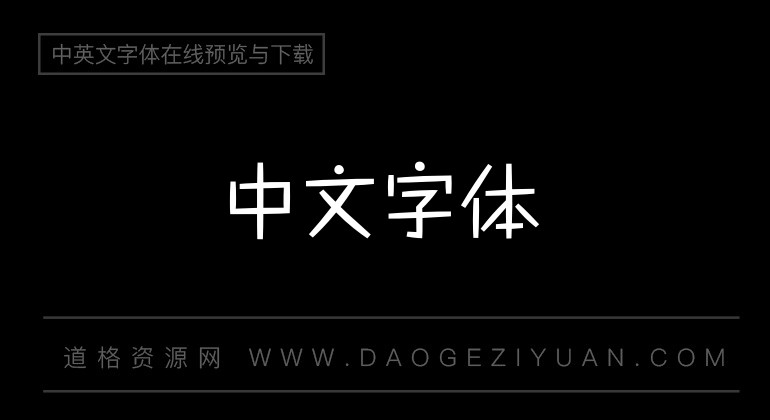
? A-OTF ソフトゴシック Std M 字体是由Adobe研发的一款日文字体,它具有清晰的线条和节奏,可以更加精确地表达文字的细节,而且字体的笔画更加自然,更加易读。该字体支持多种编码,其中包括Unicode,JIS X 0208,JIS X 0221,JIS X 0213,JIS X 0212,JIS X 0201,Shift JIS,EUC-JP,ISO 2022-JP,UTF-8,UTF-16,GB18030,HZ,BIG5,EUC-CN,ISO 2022-KR,ISO 2022-TW,ISO 2022-JP-2,ISO 2022-JP-3,ISO 2022-CN-EXT,ISO 2022-KR-EXT,ISO 2022-TW-EXT,ISO 2022-JP-EXT等。文件名:A-OTF-SoftGoStd-Medium-2.otf
A-OTF ソフトゴシック Std M是一款非常不错的手写艺术字体,具有很好的视觉感,适合于文化类的宣传设计、商业类品牌的广告和产品包装设计以及个性化文字排版等较多场景。